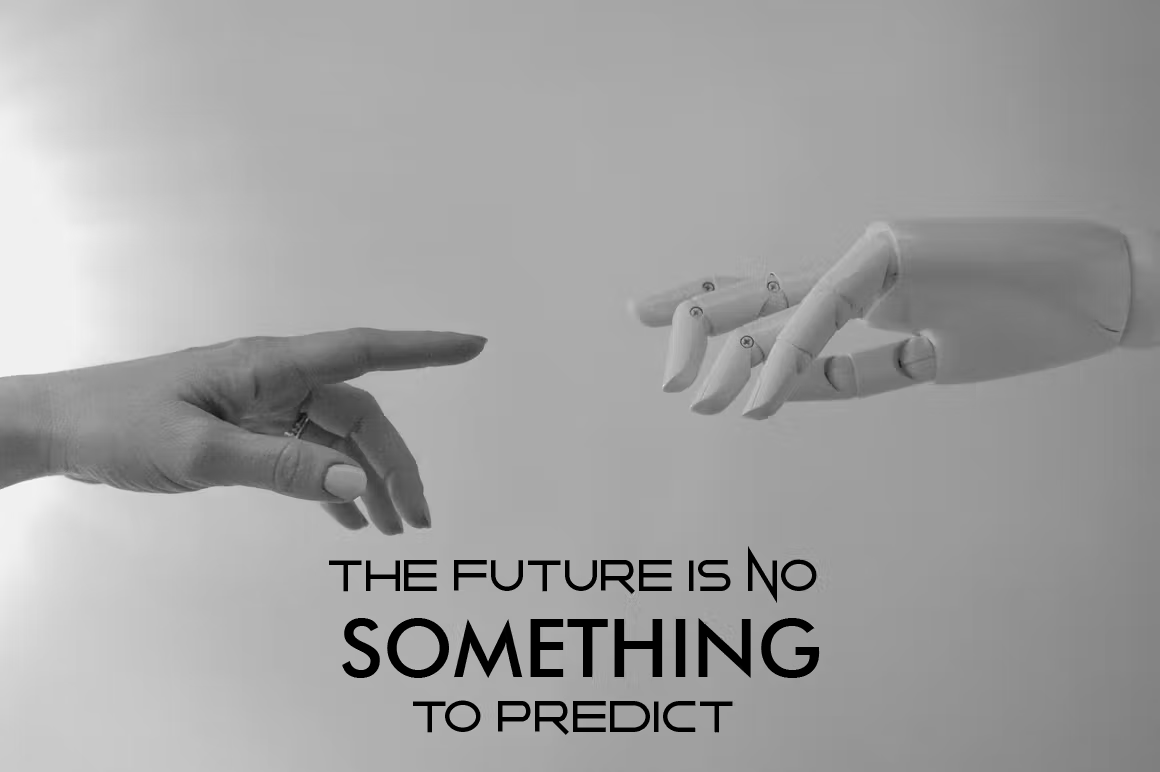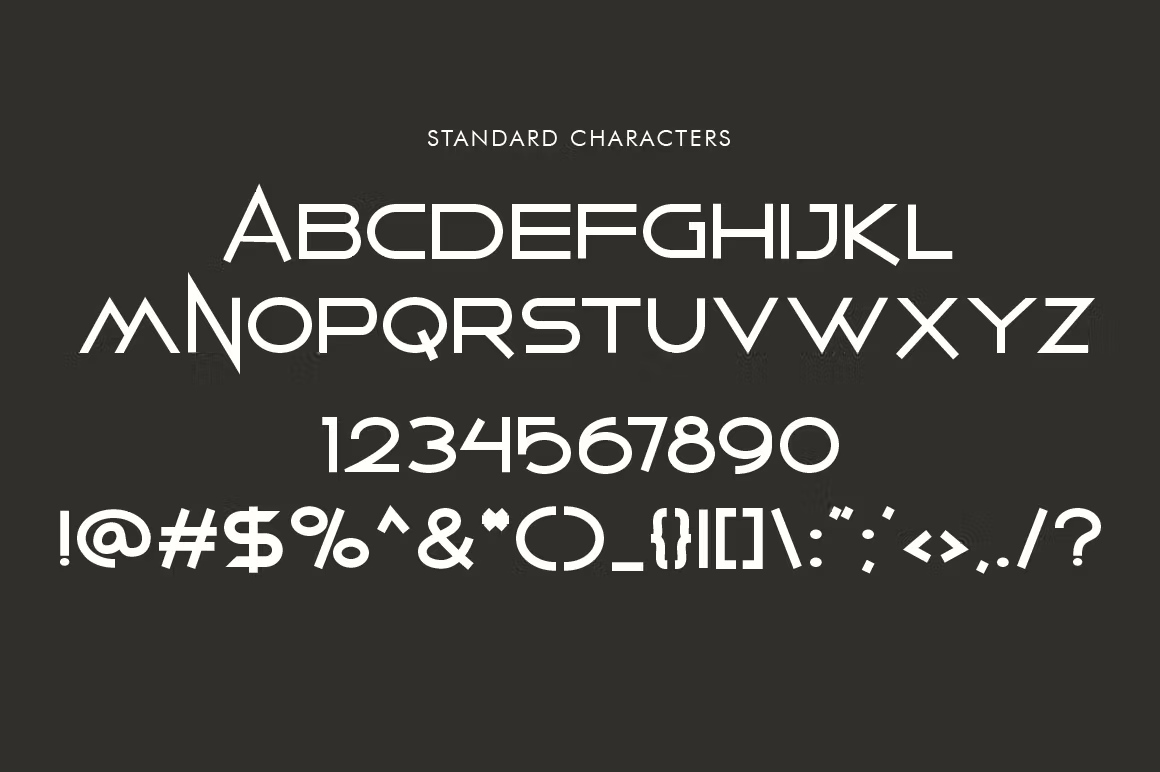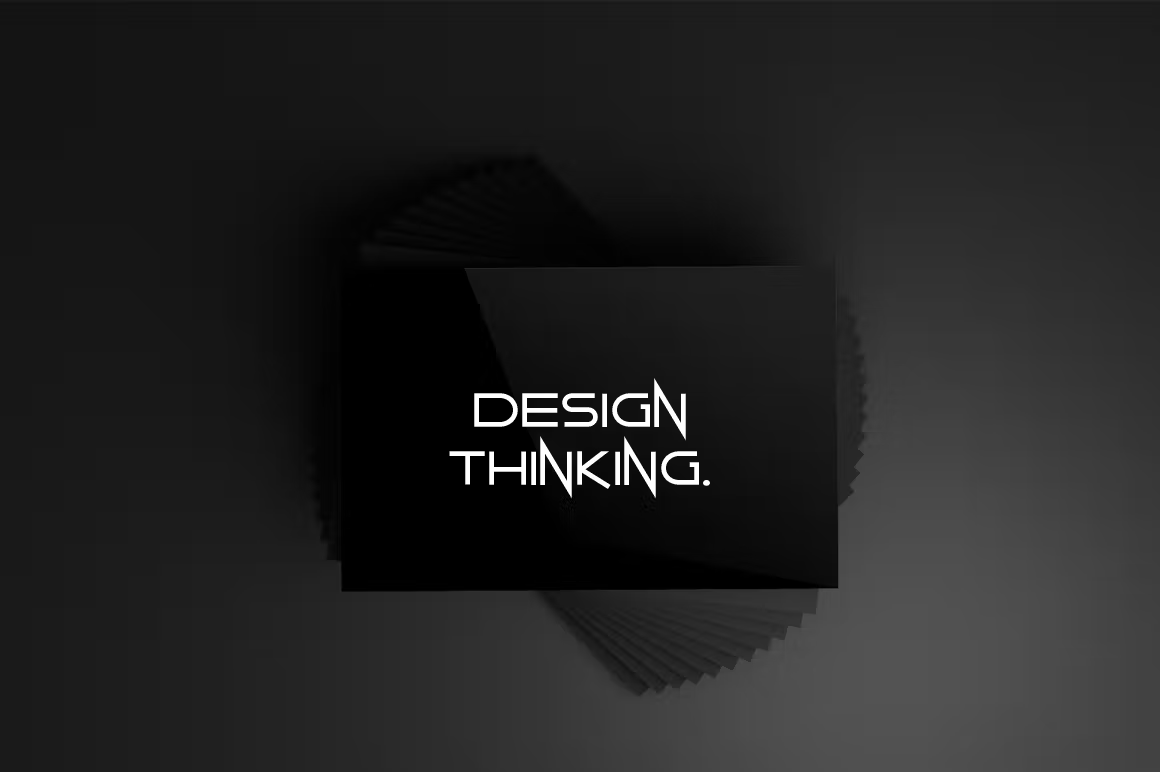
Aline Font
Description de Aline Font
Aline Font est une police sans base avec des majuscules uniques qui donneront à votre design un aspect futuriste et moderne. Vous pouvez utiliser cette police à n’importe quelle fin, notamment pour créer un logo.
Caractéristiques:
Majuscules et minuscules
Nombre
Ponctuation et symbole
Prise en charge multilingue